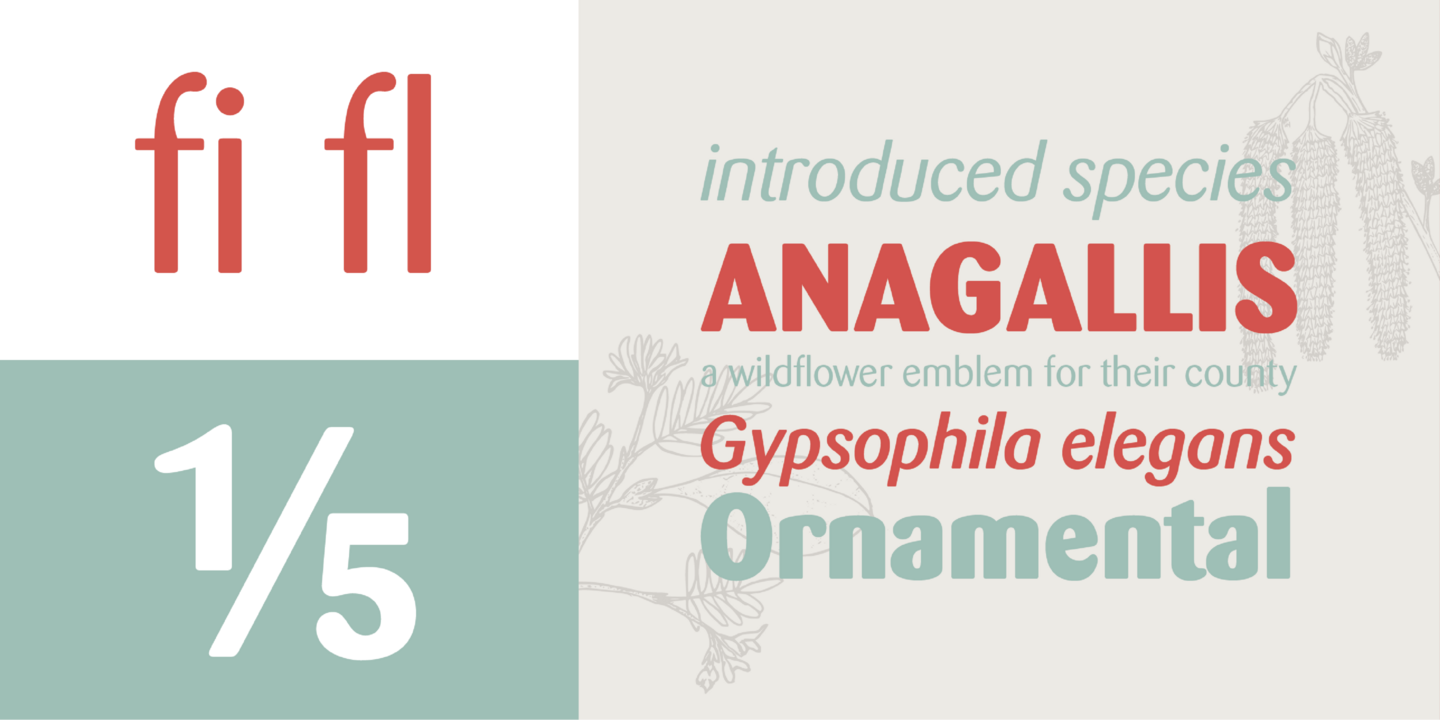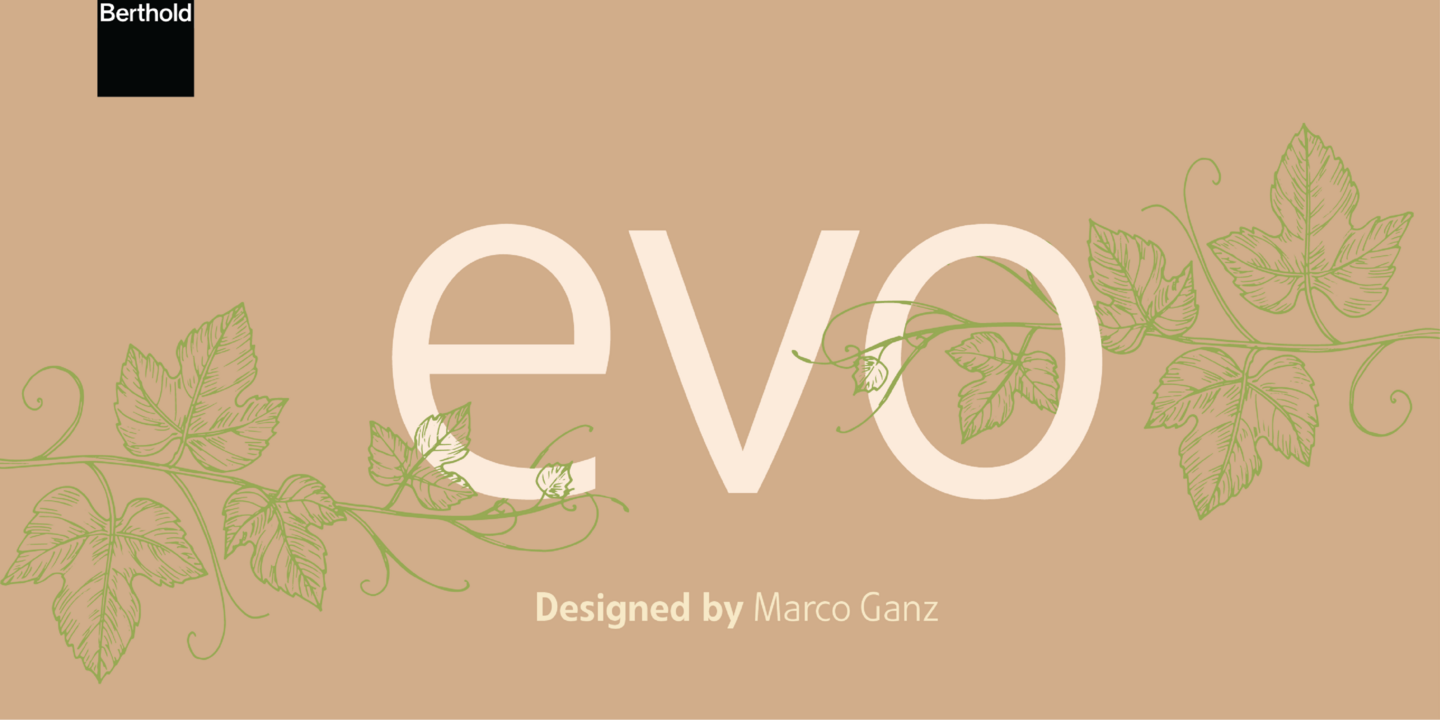
Fonts von Berthold.
H. Berthold wurde 1858 von Hermann Berthold in Berlin gegründet und stellte zunächst Druckregeln aus Messing her. Im Jahr 1893 begann das Unternehmen mit dem Gießen von Hand gesetzter Metalltypen und entwickelte sich in den folgenden 25 Jahren zu einer der größten Druckereien der Welt Foundrys . Nach dem Zweiten Weltkrieg entwickelte Berthold Maschinen für den Metallsatz und brachte 1950 seine erste Fotosatzmaschine auf den Markt.
H. Berthold AG's berühmteste Familie von Schriften, Akzidenz-Grotesk, wurde 1896 veröffentlicht. Im Laufe des 20. Jahrhunderts entwickelte die Berthold-Type Foundry die Berthold Exklusiv Collection, über 700 Schriften, die ausschließlich für die Foundry. Zu diesen Entwürfen gehören unter anderem die Familien Agora, Barmeno, Berliner Grotesk, City, Formatta, Imago, Poppl-Laudatio und Quadriga Schrift .
Beliebte Berthold Font Familien.
Hans Reichel entwarf Barmeno 1983 für H. Berthold. Diese abgerundete serifenlose Schrift hat markante Einzelzeichen, wirkt aber in Textkörpern warm, harmonisch und gut lesbar. Barmeno wird häufig für Werbetexte, Zeitschriften- und Web-Layouts verwendet. Die extrafette Strichstärke eignet sich besonders für aufmerksamkeitsstarke Überschriften.
Berthold veröffentlichte die Akzidenz-Grotesk erstmals 1896. Das Design stammt von der Royal Grotesk light von Ferdinand Theinhardt, der auch die Normal-, Mittel- und Fettschnitte lieferte. Im Laufe der Jahre hat Berthold diese äußerst beliebte und vielseitige Familie erweitert. AG Super wurde 1968 von Günter Gerhard Lange entwickelt und eignet sich hervorragend für Überschriften. Im Jahr 2001 entwickelte Günter Gerhard Lange hinzugefügt am weitere Schnitte für Berthold, darunter Super Italic und Extra Bold italic.
Günter Gerhard Lange hat die Akzidenz-Grotesk-Familie neu gezeichnet und H. Berthold hat sie 1983 als AG Schoolbook herausgebracht. Diese zeitgemäßere Version des Akzidenz-Grotesk-Designs bietet markante, alternative Zeichen für a, k, l, u, y, G, I, J, K, M und R. Die AG Schoolbook ist für ihre Klarheit und Lesbarkeit bekannt.
Die ersten ägyptischen oder Slab-Serifen, die auf Aufmerksamkeit und Wirkung in der Werbung abzielen, erschienen zu Beginn der industriellen Revolution (1800er Jahre). Nach dem Ersten Weltkrieg wurden sie wieder populär. 1930 brachte Berthold die City von Georg Trump heraus, ein markantes, rechteckiges Design, das ein sportliches, urbanes Gefühl hervorruft.
Berthold
1997 erwarb Berthold Types, ein in Chicago ansässiges Unternehmen, die Urheber-, Marken- und Designrechte an der Sammlung Berthold Exklusiv. Günter Gerhard Lange, von 1961 bis 1990 künstlerischer Leiter von Berthold, war für einen Großteil der Gestaltung und Produktion der Berthold Exklusiv verantwortlich. 1991 trat Bernd Möllenstädt die Nachfolge Langes als Schriftleiter der Sammlung Berthold Exklusiv an und leitete die Digitalisierung der Entwürfe.
Im Jahr 2022 erwarb Monotype die historische Bibliothek von Berthold Schrift . Die Verwaltung durch Monotype wird die weltweite Sichtbarkeit des Berthold-Bestandes erhöhen, sein Erbe feiern und diese wichtige Schriften in die Hände von mehr Kreativen bringen.
Designer
H. Berthold
Der 1831 geborene Hermann Berthold war der Sohn eines Kalikodruckers. Die meisten deutschen Buchdrucker und viele Drucker im Ausland gaben ihre Aufträge bei Berthold in Auftrag. Seine Produkte wurden so beliebt, dass sich im Druckgewerbe der Spruch "So präzise wie Berthold-Messing" durchsetzte. Hermann Berthold war bis 1888 Leiter der Bertholdschen Schriftgießerei.
Designer
Günter Gerhard Lange
Der renommierte Handwerksmeister Günter Gerhard Lange wurde am 12. April 1921 in Frankfurt an der Oder, Deutschland, geboren. 1961 ernannte Berthold Lange zu seinem künstlerischen Leiter. 1971 wurde Lange in den Vorstand von Berthold berufen, was die Bedeutung der Schrift bei Berthold bestätigte. Als die treibende Kraft hinter dem Berthold-Schriftenprogramm von 1961 bis 1990 war Lange verantwortlich für die Kreation, die sorgfältigen Produktionsstandards und die Aufmerksamkeit für Qualität, die in jedem der Berthold Exklusivs
Designer
Albert Boton
Der 1932 geborene Albert Boton studierte Grafikdesign und belegte Kurse in Kalligrafie bei Adrian Frutiger. Später arbeitete er als Schriftgestalterlehrling bei der Druckerei Deberny & Peignot Foundry in Paris unter Adrian Frutiger. Berthold veröffentlichte Boton (1986) und Agora (1990) im Rahmen des Berthold Exklusivs Programms.
Designer
Dieter Hofrichter
Der langjährige Assistent und Schützling von Günter Gerhard Lange, Dieter Hofrichter, wurde in Mannheim, Baden-Württemberg, Deutschland, geboren. Im Jahr 2000 brachte Berthold eine gemeinsame Arbeit von Lange und Hofrichter heraus, einen Scotch-Typ namens "Whittingham". Zu den weiteren Beiträgen von Hofrichter gehören die Veröffentlichung der verbesserten Akzidenz-Grotesk und die Veröffentlichung der Futura BQ.